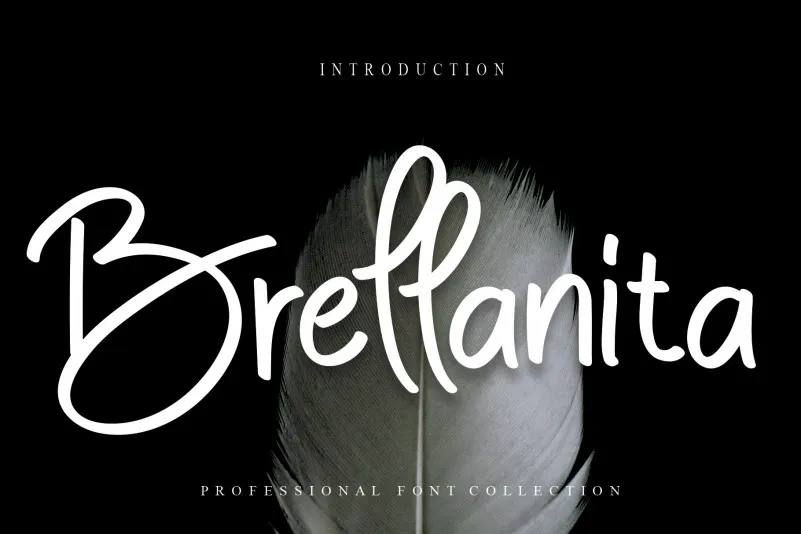
Brellanita Script Font – Download Grátis
A fonte Brellanita Script é uma escolha perfeita para quem busca emoção e sofisticação ao imprimir textos criativos. Com sua graça natural e detalhes cuidadosamente projetados, a Brellanita Script oferece um estilo elegante que transmite personalidade e originalidade. Ideal para uso em materiais de design gráfico como cartazes, logotipos, efeitos visuais ou qualquer outro aplicação onde você deseja dar uma carona aos seus projetos com um toque especial. Ela é perfeita tanto para usuários profissionais quanto para criativos iniciantes que buscam destacar-se em seus trabalhos de design. Como a própria fonte, a Brellanita Script destaca a sua capacidade única e inovadora. E você? Que papel ela pode desempenhar no seu próximo projeto visual?